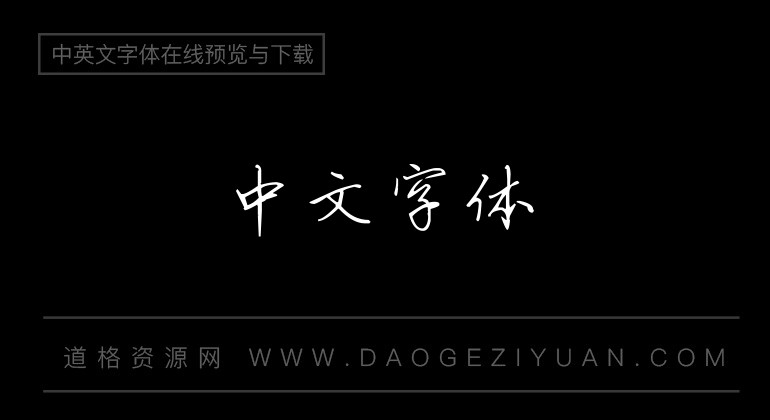
英章行书
英章行书是一种经典的中国书法字体,是宋代书法家顾炎武所创,也叫顾炎武行书或顾炎武字体。它是以宋代书法家顾炎武的书法为基础,结合当时书法中的其他流派而形成的一种独特的书法字体。它以简洁大气、笔势流畅、笔画挺拔、结构清晰、对称性强、风格稳重、节奏感强等特点而闻名于世。英章行书的笔画结构清晰,挥洒自如,笔势优美,笔画挺拔,且节奏感强,具有很强的视觉冲击力,能把书法文字表现得极为生动、灵动、绚丽多彩。
英章行书是一款非常不错的手写艺术字体,具有很好的视觉感,适合于文化类的宣传设计、商业类品牌的广告和产品包装设计以及个性化文字排版等较多场景。
英章行书字符映射图